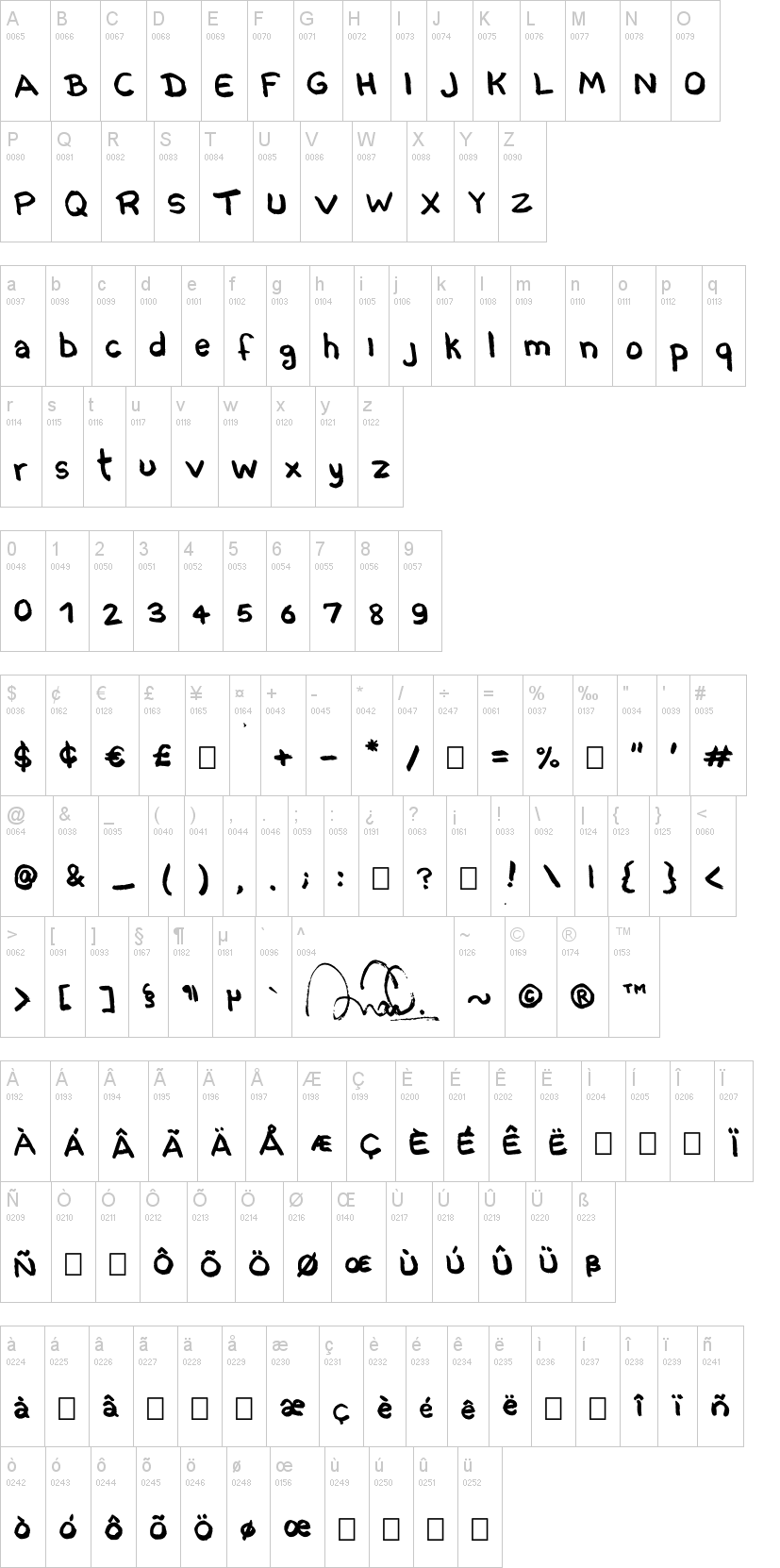
Note of the authorPour les dessinateurs de bande dessinée. Celle-ci est inspirée des phylactères de vieux albums vintage en noir et blanc des années 1930-35. Font for cartoonist. Enjoy !